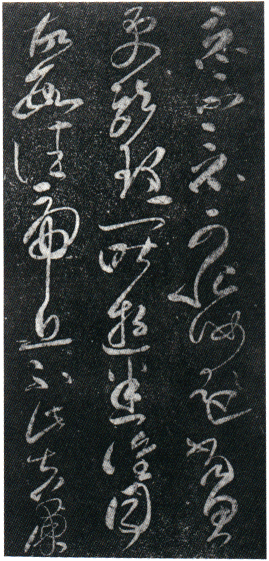
张芝
张芝简介
生年不详,约卒于汉献帝初平三年(约公元192年),敦煌酒泉(今属甘肃)人,字伯英,善章草,后脱去旧习,省减章草点画、波桀,成为“今草”,张怀瓘《书断》称他“学崔(瑗)、杜(操)之法,因而变之,以成今草,转精其妙。字之体势,一笔而成,偶有不连,而血脉不断,及其连者,气脉通于隔行”,三国魏书家韦诞称他为“草圣”。晋王羲之对汉、魏书迹,惟推钟(繇)、张(芝)两家,认为其余不足观。对后世王羲之、王献之草书影响颇深。
张芝刻苦练习书法的精神,历史上已传为佳话。晋卫恒《四体书势》中记载:张芝“凡家中衣帛,必书而后练(煮染)之;临池学书,池水尽墨”。后人称书法为“临池”,即来源于此。尤善章草,有"草圣"之誉,当时的人珍爱其墨甚至到了"寸纸不遗"的地步。评价相当高,尤以草书为最。
唐 张旭(芝) 冠军帖草书25x66宋拓本